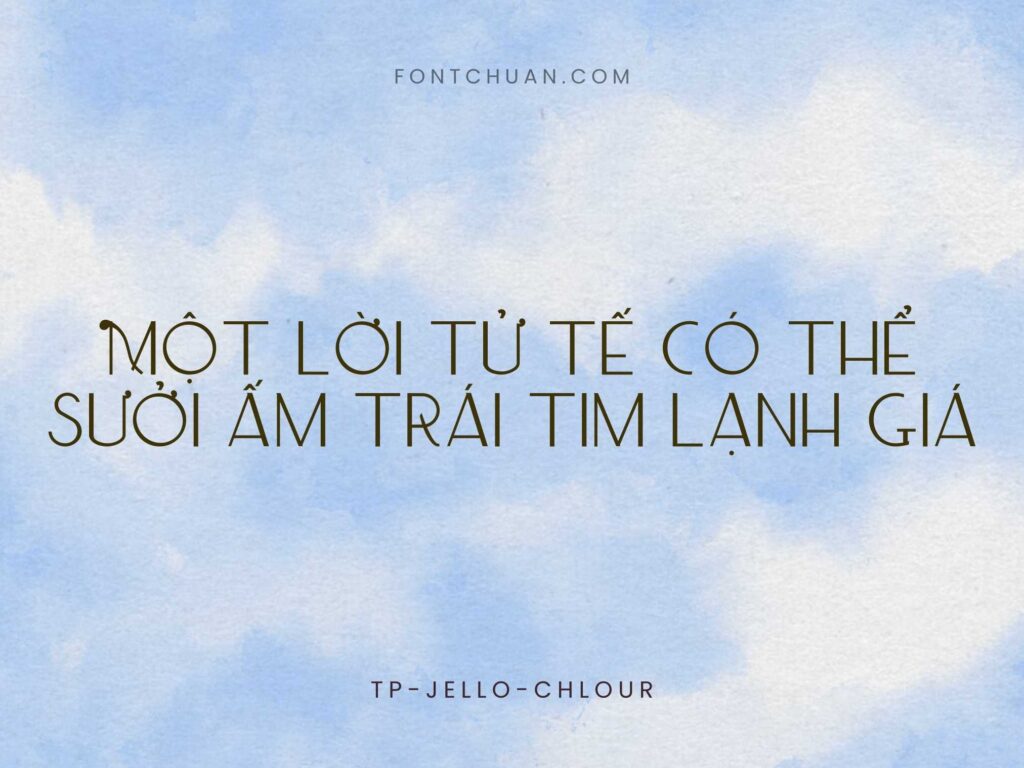
Font TP Jello Chlour Việt Hóa
Jello Chlour là một font chữ trưng bày mang phong cách hiện đại và thanh lịch, được thiết kế bởi Jolicia Type. Với cấu trúc tinh tế và đa dạng các phiên bản như Light, Regular, Semi Bold, Bold và Script, đây được xem là một Font chữ quảng cáo lý tưởng dành cho những dự án cần sự nổi bật và chuyên nghiệp. Font đã được Việt hóa để hỗ trợ tiếng Việt bởi Tuỳn Pucca, mở rộng khả năng sử dụng cho người dùng Việt Nam. Font này được sưu tầm và chia sẻ bởi thành viên của Font Chuẩn, đáp ứng nhu cầu sử dụng trong các dự án thiết kế đa dạng.
Đặc điểm thiết kế của Jello Chlour bao gồm các đường nét tinh tế và hiện đại, tạo cảm giác sang trọng và chuyên nghiệp. Font này phù hợp cho các ứng dụng như xây dựng thương hiệu, thiết kế logo, thiệp mời và các dự án sáng tạo khác. Các ngành nghề phù hợp bao gồm quảng cáo, nghệ thuật và thiết kế đồ họa.